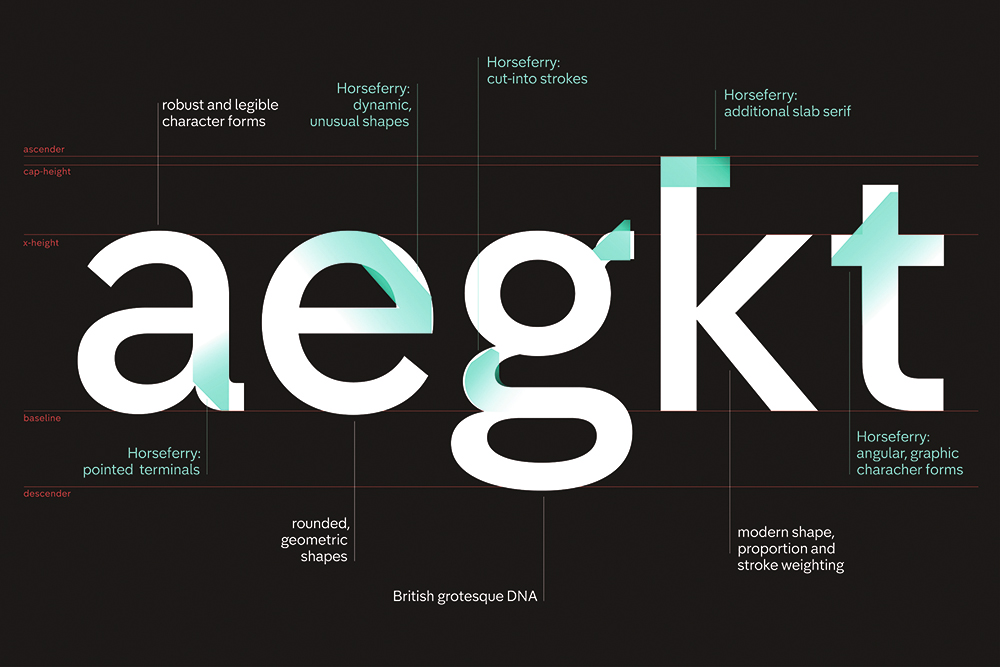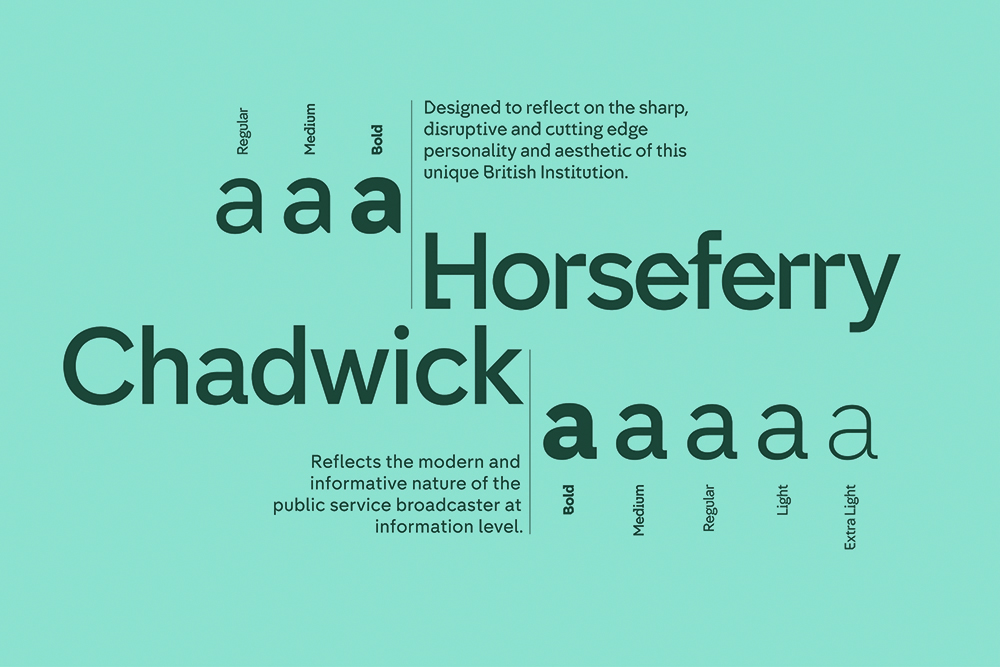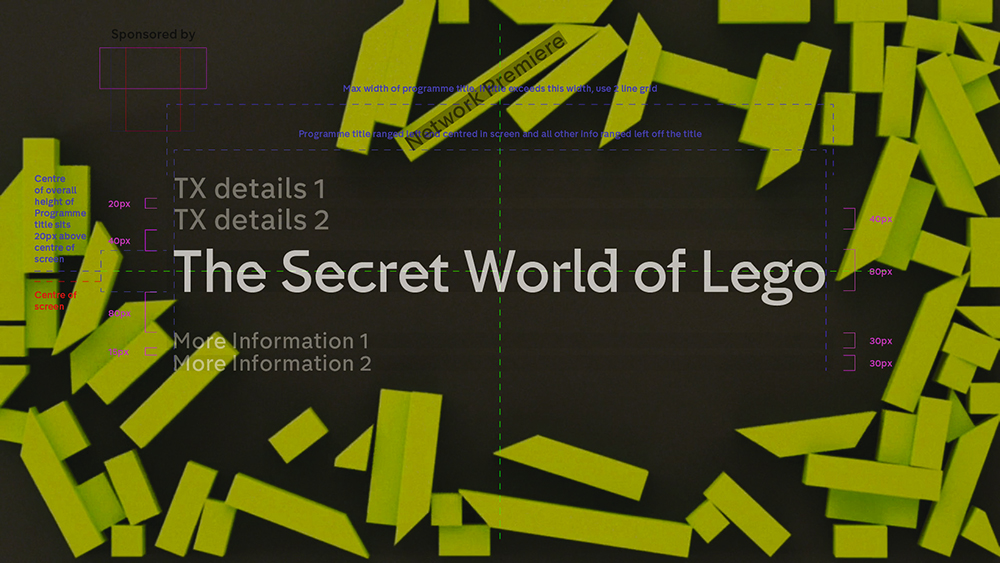
채널4의 새로운 타입페이스 : 블록들의 향연
영국 공영방송 채널4의 디자인팀인 포크리에이티브(4 Creative)는 채널 4를 리브랜딩하기로 결정했고, 이에 이전부터 채널 4와 친분을 쌓아 온 스튜디오 DBLG가 전반적인 진행을 맡았다. 이들은 아이덴츠 광고에서 아예 ‘4’를 없애 버리는 방안을 구상하며 램비 네언(Lambie Nairn)이 만든 기존의 ‘4’ 로고를 9개의 블록으로 완전히 해체시키는 아이디어를 제시했다. 또한, 리브랜딩의 일환으로 새로운 타입페이스도 제작하기로 했다.
채널4(CHANNEL 4)의 새로운 타입페이스 : 블록들의 향연
DBLG의 그랜트 길버트(Grant Gilbert)는 함께 작업할 만한 폰트 디자이너들의 목록을 짰다. 채널 4의 예전 타입페이스는 당시 TV에서 보기에 매우 신선한 것이었다. 그래서 이들은 이번에도 같은 결과를 내고 싶었다. 네빌 브로디(Neville Brody)에게 연락을 취했고 그에게 그때까지 만든 광고 영상들을 보여주었다. 그가 이끄는 브로디 어소시에이츠는 작업 방식과 아이디어 면에서 정말 완벽한 팀이다. 네빌, 루크 프라우즈(Luke Prowse), 잭 르웰린(Jack Llewellyn)은 블록의 형태에서 힌트를 얻어 두 개의 타입페이스를 만들었다. 아무래도 특이한 호스페리(Horseferry)가 사람들의 주목을 많이 받았지만 정보 전달용인 채드윅(Chadwick)도 아름다운 타입페이스다.
이번 리브랜딩 작업에서 포크리에이티브는 기존 램비 네언의 ‘4’ 로고에 약간의 변화를 주었다. 블록들 사이에 간격을 둠으로써 단순한 숫자를 넘어 눈길을 사로잡는 인상적인 형태를 창조한 것이다. ‘4’가 온전하게 드러난 이 로고는 방송이 아닌 영역에서 사용될 것이었다.
채널 4의 두 가지 새 타입페이스인 채드윅과 호스페리에 대해 네빌 브로디가 설명한다.
“채널 4는 매우 영국적인 브랜드입니다. 독립성과 창의성이 풍부한 나라답게 우리 영국인들은 아무리 노력해도 착하게 굴 수가 없죠. 채널 4가 영국 문화계에 가져온 중요한 변화 중 하나는 아이디어가 계층 구조와 관계없이 어디에서나 나올 수 있다는 점을 각인시켰다는 것입니다.
채널 4와 반나절 함께 논의하면서 그들이 원하는 것을 달성할 수 있는 다양한 방법을 모색했습니다. 우리는 영국 고딕 전통에서 영감을 얻었고 모더니즘과 기하학적 타입페이스도 약간씩 참조했습니다. 또한, 영국의 교통 표지판 디자인을 맡은 그 위대한 마가렛 칼버트(Margaret Calvert)로부터도 영향을 받았죠.
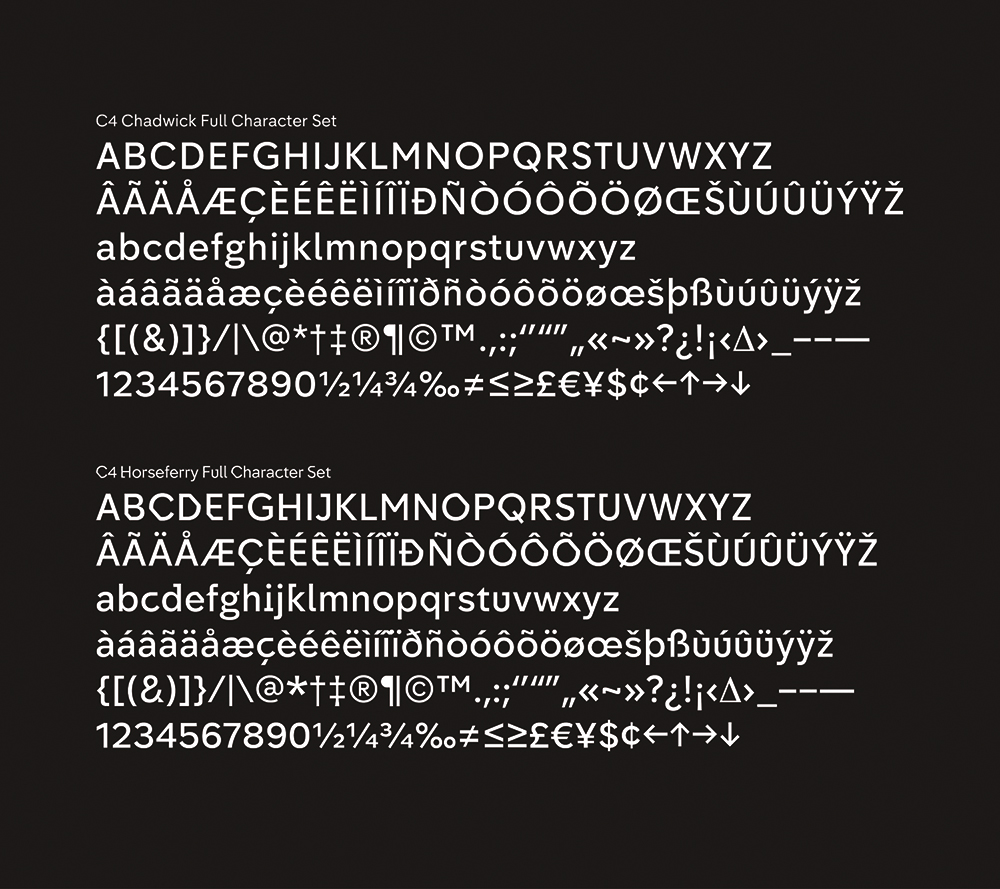
우리는 깔끔하고 직접적인, 그래서 뉴스나 스포츠 등에 사용될 타입페이스가 필요했는데 그래서 만든 것이 채드윅입니다. 그리고 헤드라인에 사용될 과감하고 개성 강한 타입페이스로는 호스페리를 만들었습니다. 우리는 각각 영국적 특성이 충분히 반영된 7개 내지 8개의 서로 다른 타입 패밀리를 갖추고 싶었습니다. 이 타입 패밀리들을 모두 제공하고 싶었지만 간략하게 한 묶음으로 나열해서 보여주는 것에 만족해야 했습니다.
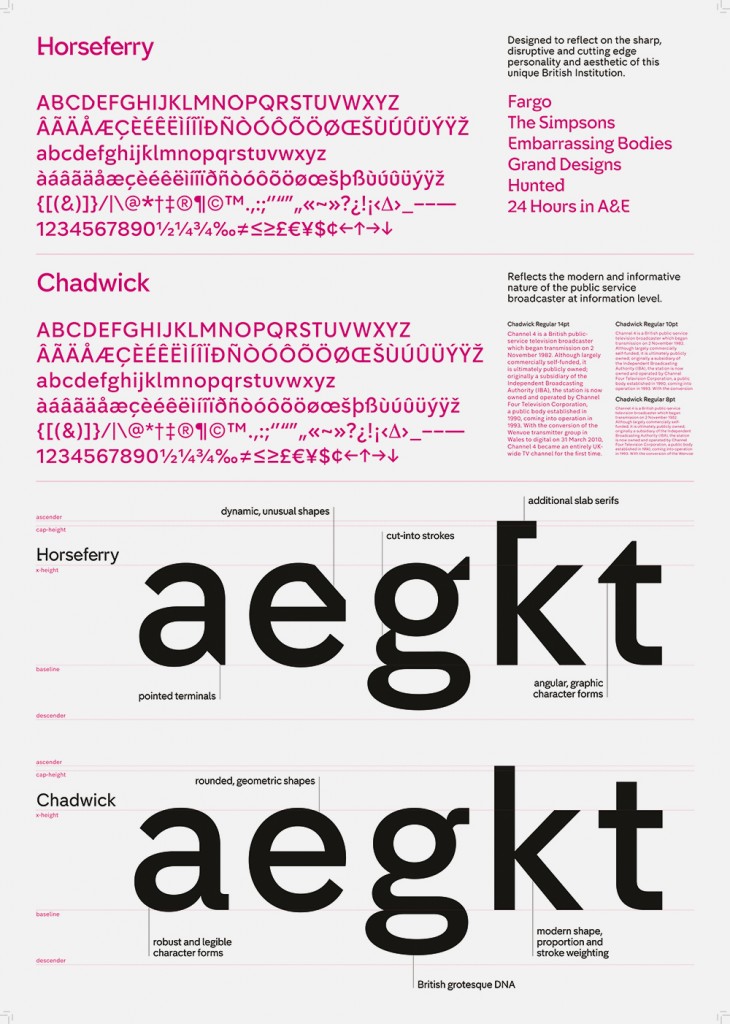
직접 스케치를 해서 프린트하기도 했고 바로 디지털 스케치를 하기도 했습니다. 우리가 사용한 소프트웨어는 글립스(Glyphs)였어요. 그 전까지는 폰트랩 스튜디오(FontLab Studio)를 주로 사용했었죠. 창조적인 관점에서 우리는 무엇이든 할 수 있었지만 전체적인 균형을 맞춰야 한다는 점에서는 어려움을 느꼈습니다.”
헤드라인용 폰트인 호스페리는 끝이 뾰족하고 각이 큰 형태의 슬랩 세리프다.
호스페리는 영국 고딕 양식과 블록들의 각도에서 영감을 얻어 만들어졌다.
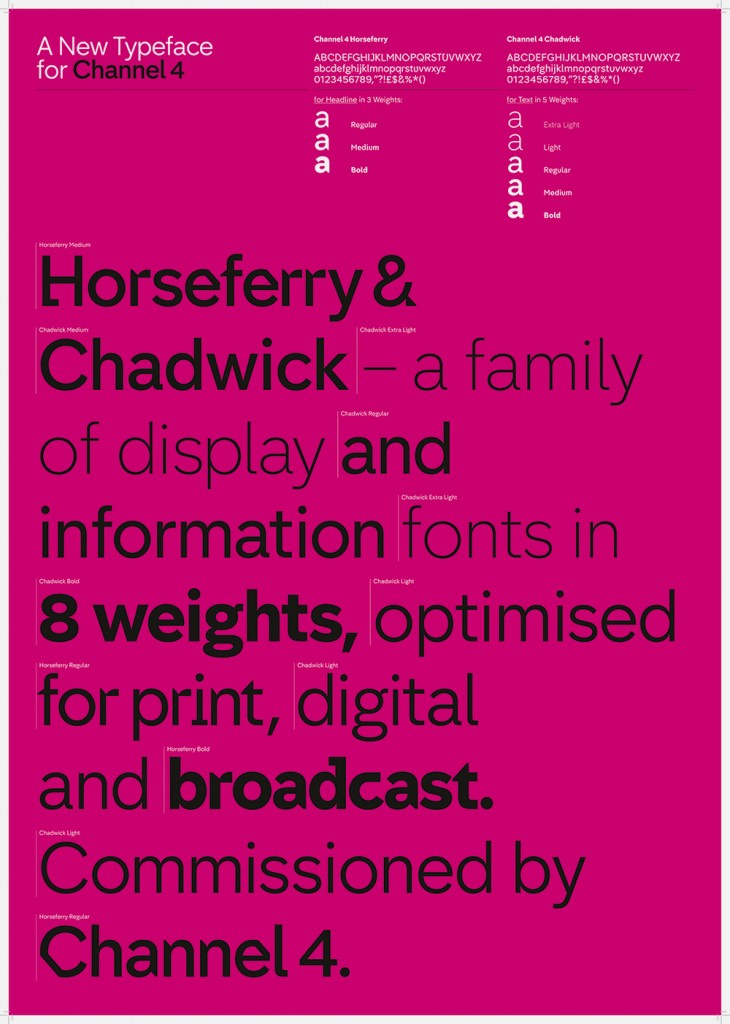
새 타입페이스들을 8가지 다른 굵기로 한눈에 보여주는 포스터
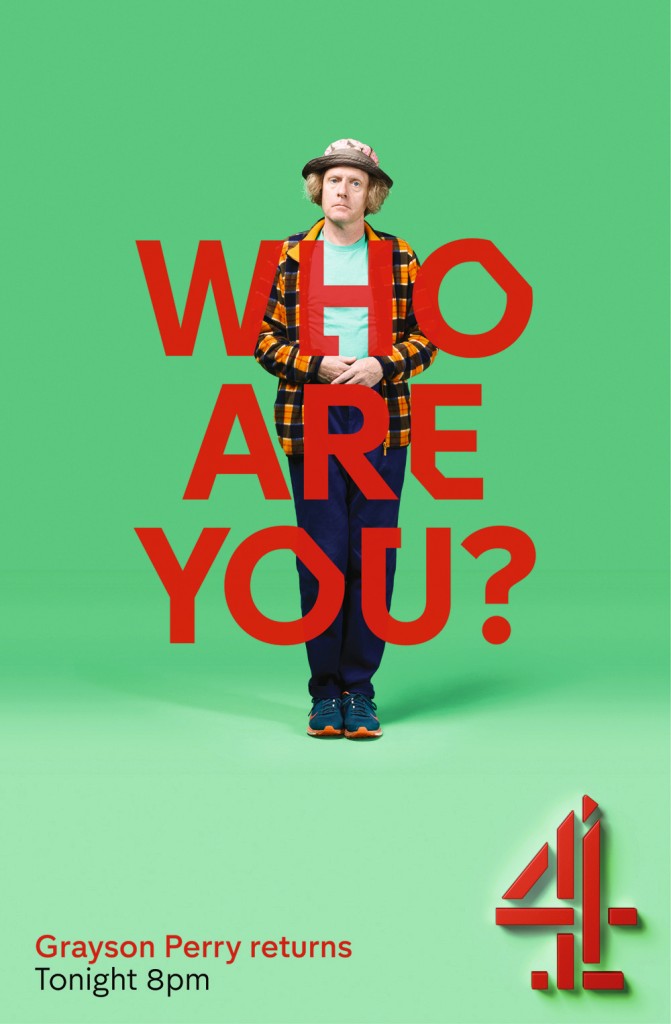
포크리에이티브가 만든 포스터에 등장한 호스페리 타입
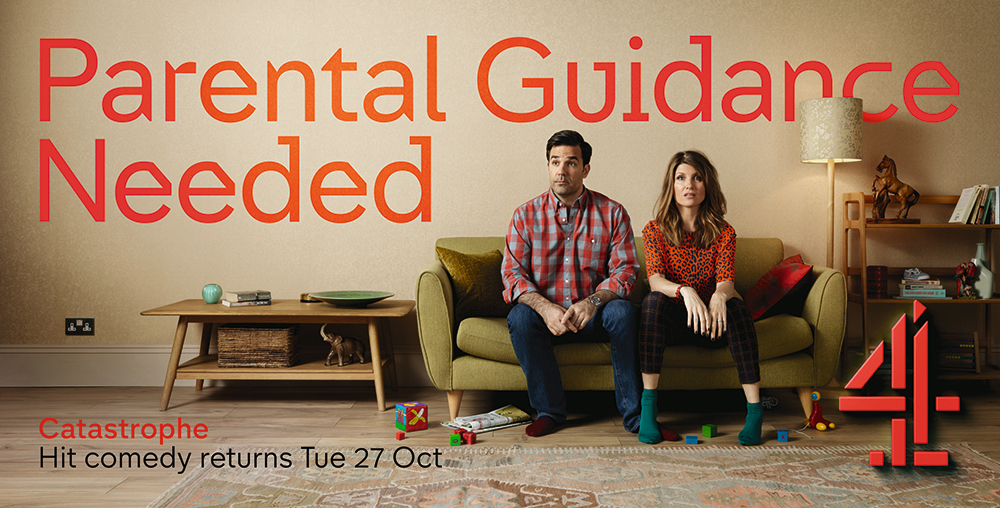
개성 넘치는 타입페이스 덕분에 포크리에이티브는 포스터 색상을 자유롭게 선택할 수 있었다.